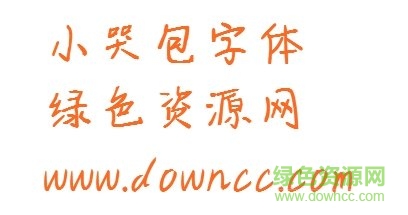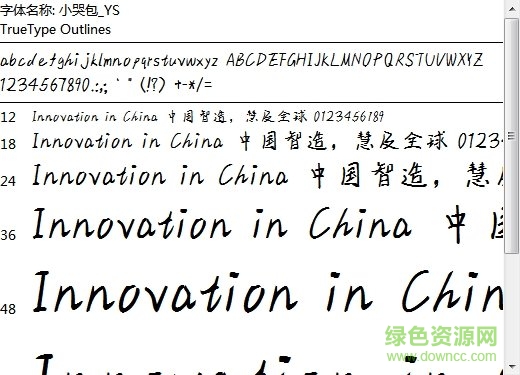
小哭包字體是從手機qq里面提取出來的一款可愛卡通字體,字跡小巧靈動,給人十分悅目清晰的視覺體驗,讓你任意揮灑你的自信和清揚,喜歡的朋友就來綠色資源網(wǎng)試試吧!
簡潔清晰而不造作、溫暖柔軟而不剛硬,這款字體如其名字一般,給人一種童趣憨厚的可愛視覺,讓你從字里行間里面都能找到一種小美好,可以適用在平面設(shè)計等多個領(lǐng)域!